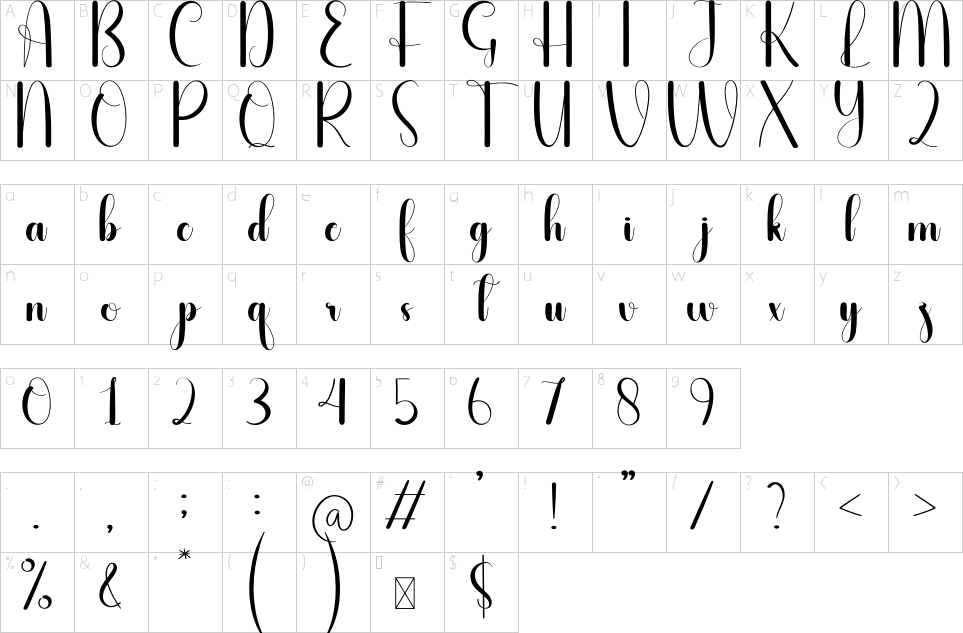
Dolly Font – Fonte Grátis
Dolly Font
Descubra a tranquilidade e simplicidade na escrita com Dolly Font. Desenvolvida pelo designer William Jhordy, essa fonte está disponível gratuitamente tanto para Windows quanto para Mac. A Dolly oferece um equilíbrio perfeito entre elegância e facilidade de uso, tornando-a uma opção ideal não apenas para designers iniciantes, mas também para quem busca um acabamento neutro em texturas variadas. Com seus 361 downloads, é claro que muitos já estão adotando a Dolly Font na sua paleta de recursos gráficos, destacando seu charme e versatilidade. Para aqueles buscando um texto limpo e moderno para seus projetos digitais, Dolly pode ser o elemento perfeito para finalizar seu projeto com classe.
Mapa de caracteres da fonte Dolly Font